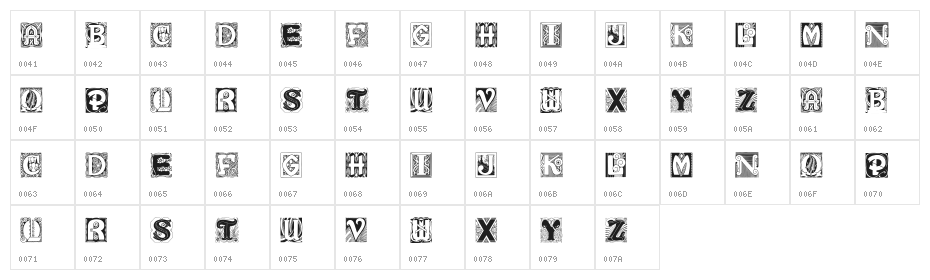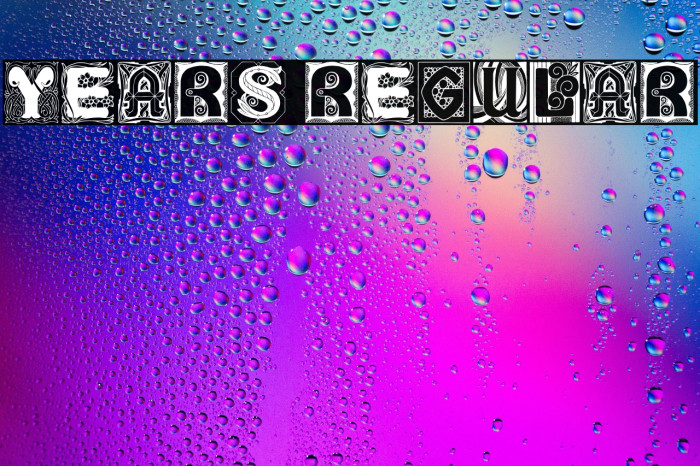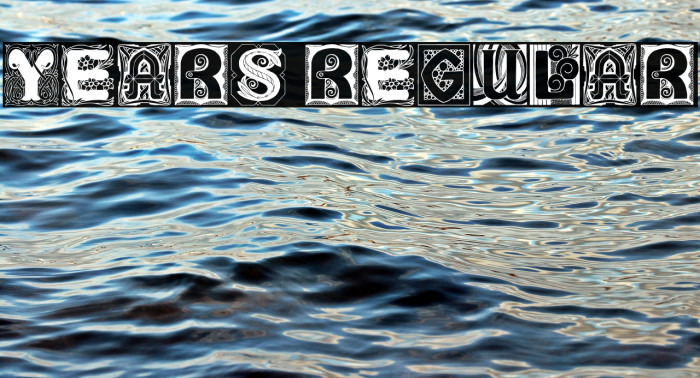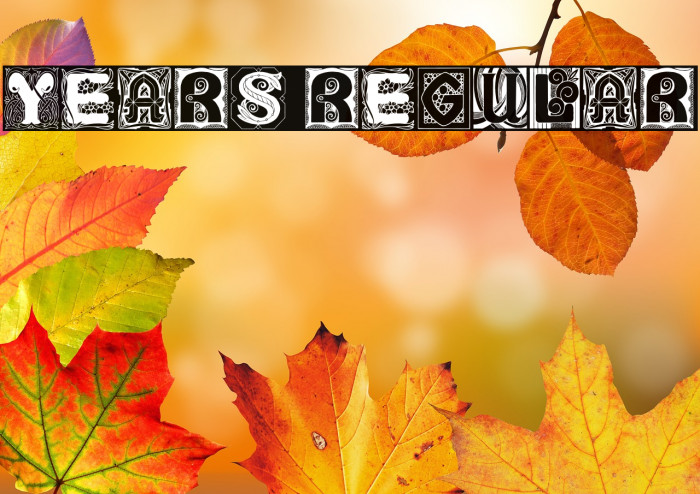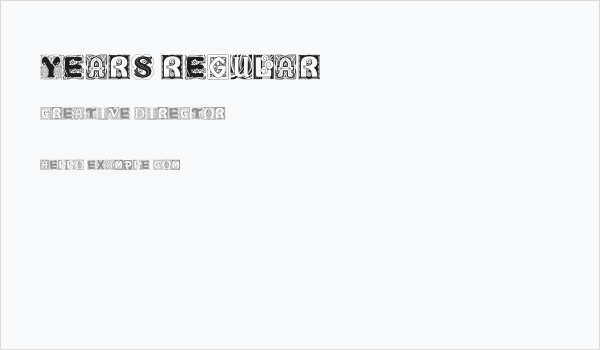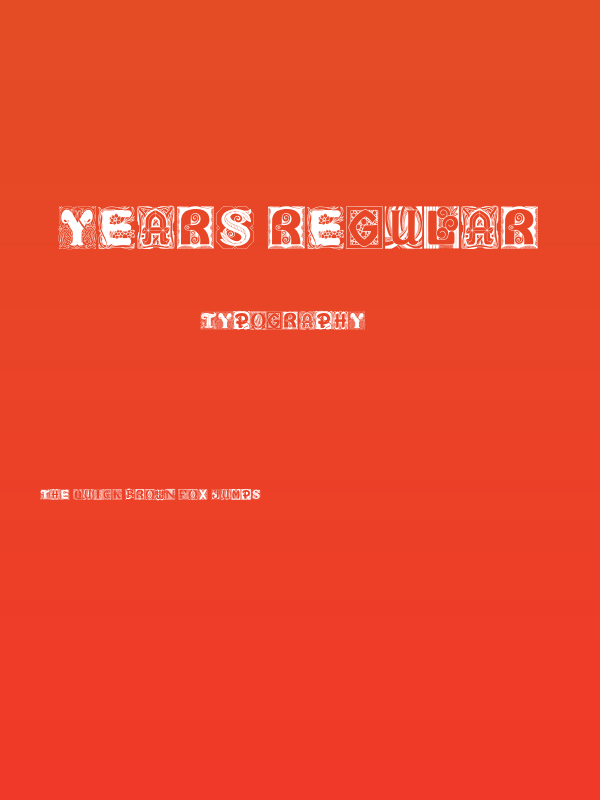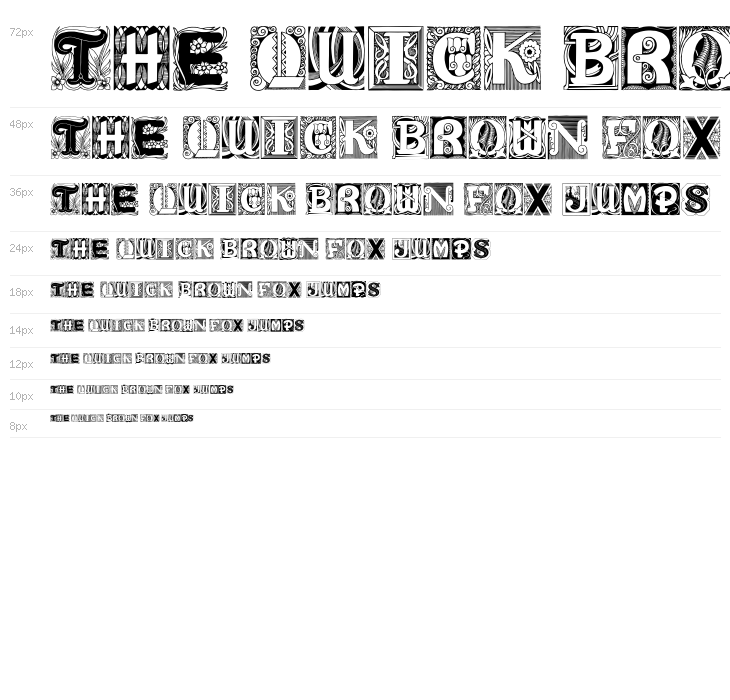
Years Regular Font
✎ Retro
| Progetti proposti | Ideal for use in invitations, posters, book covers, and branding projects that require a vintage or artistic touch. |